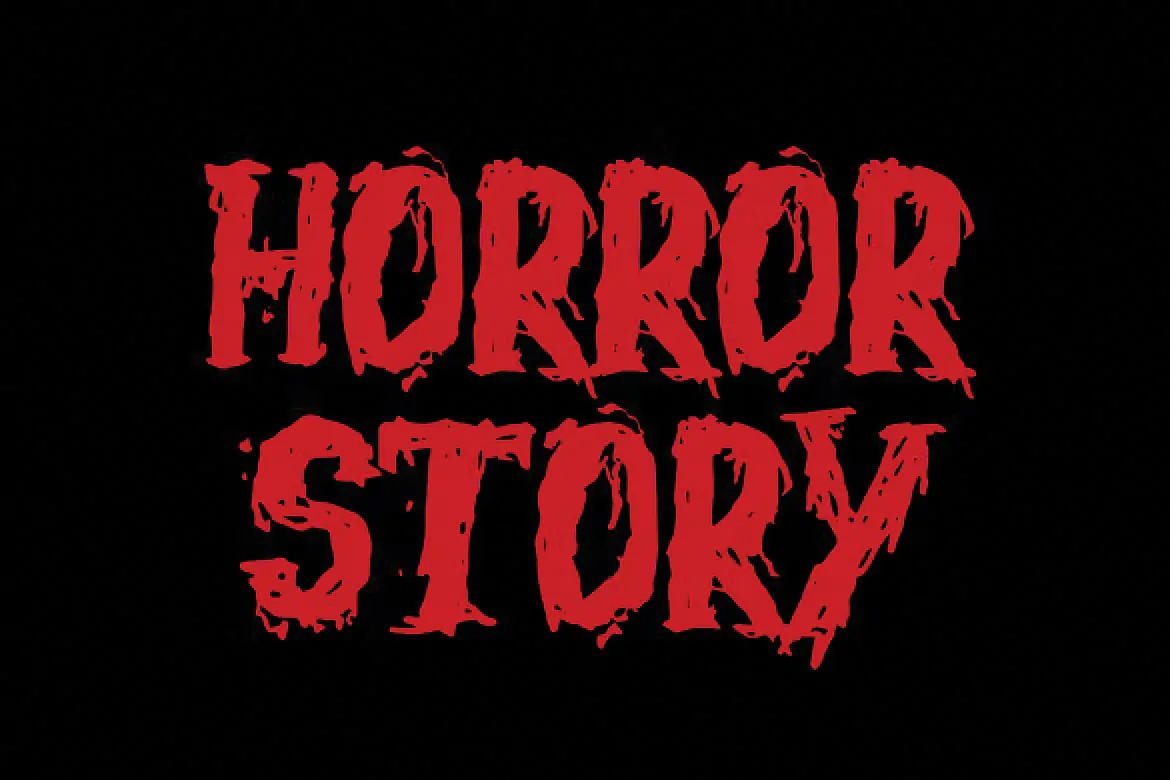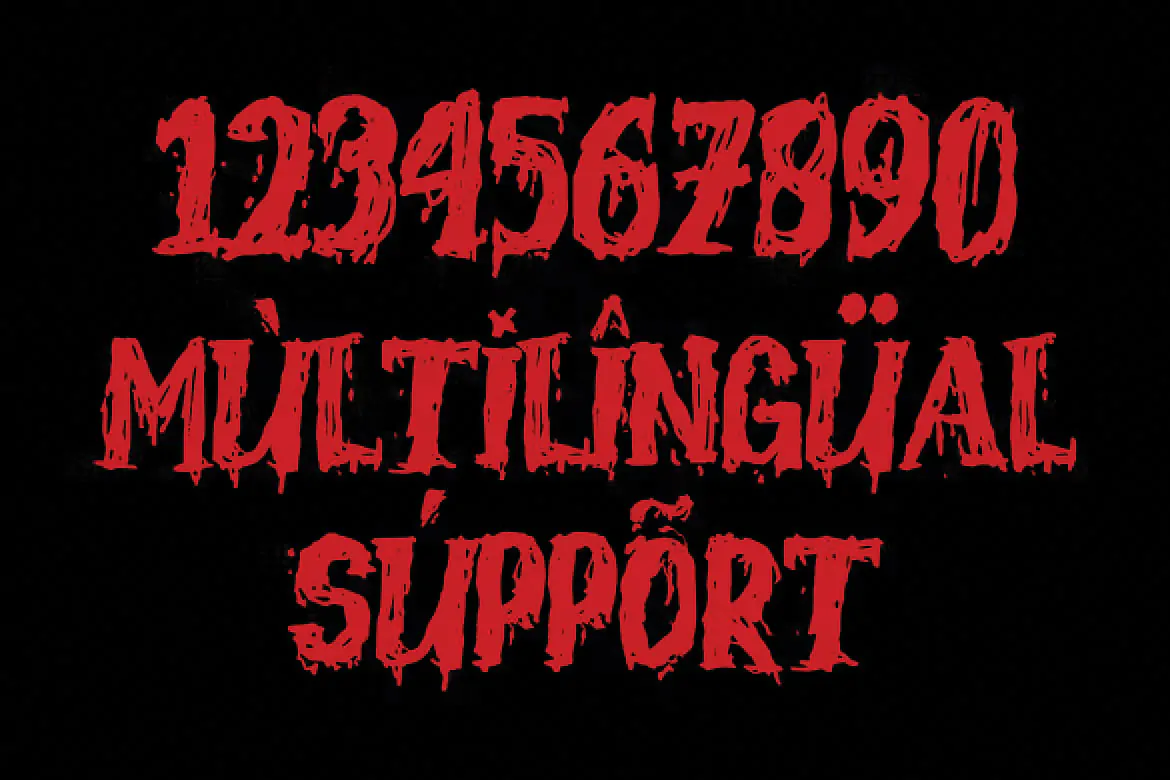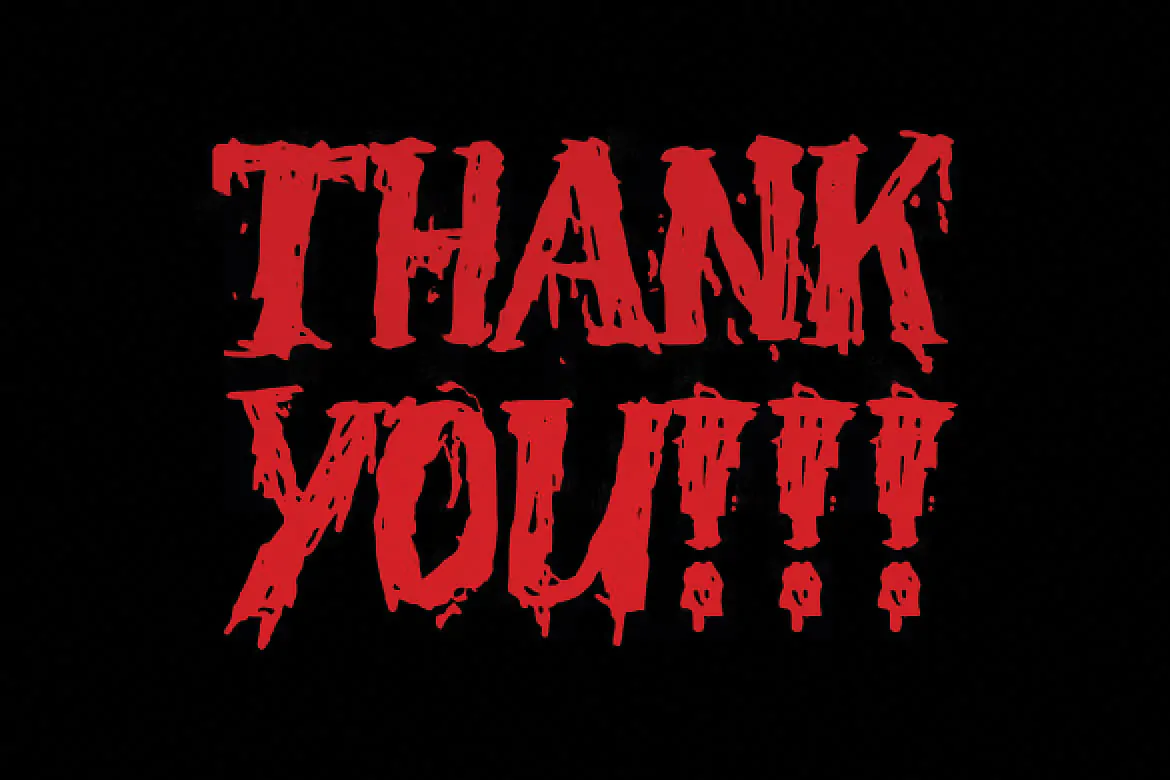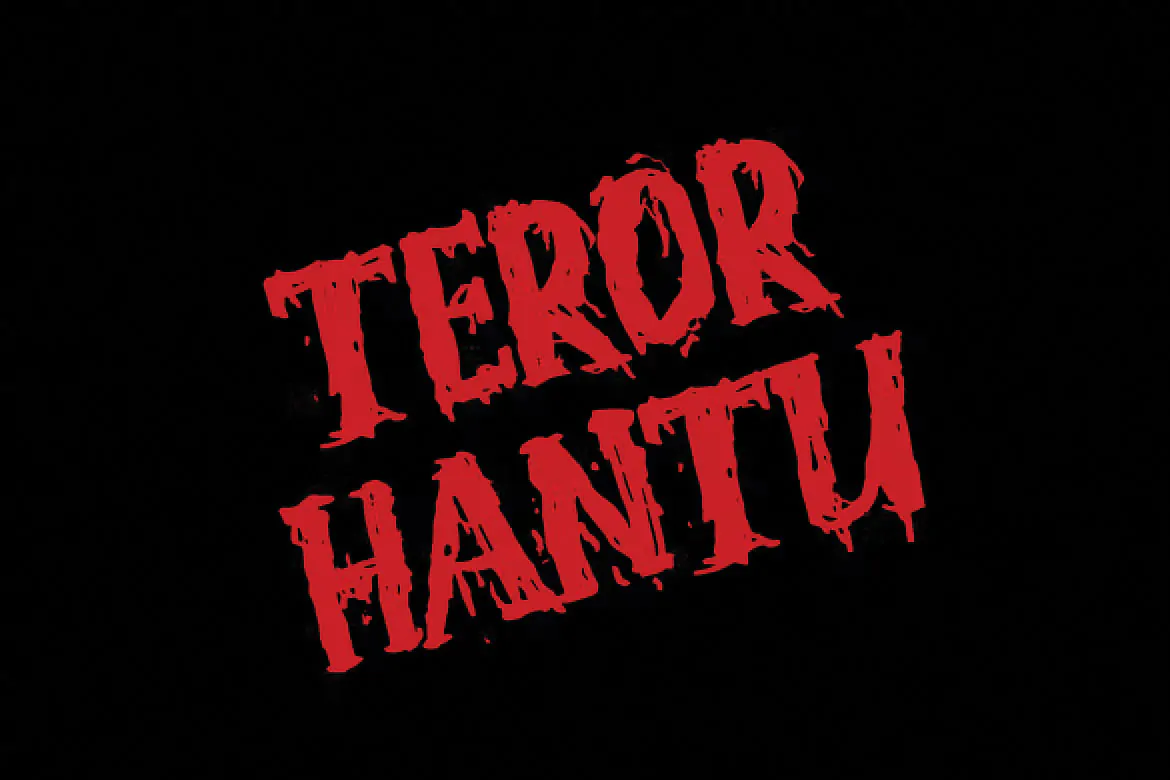
فونت ترسناک خونی Tumbal Cinta
فونت ترسناک خونی انگلیسی
فونت ترسناک خونی Tumbal Cinta یک قلم تزئینی انگلیسی فوق العاده زیبا است که مناسب جهت استفاده در طرح و پروژههای گرافیکی مختلف به خصوص پوسترهای هالووین میباشد. این قلم زیبا با وزن معمولی طراحی شده است که میتوانید از آن در طراحی انواع پوستر، بنر، بسته بندی محصولات، ظروف یکبار مصرف و … میباشد.